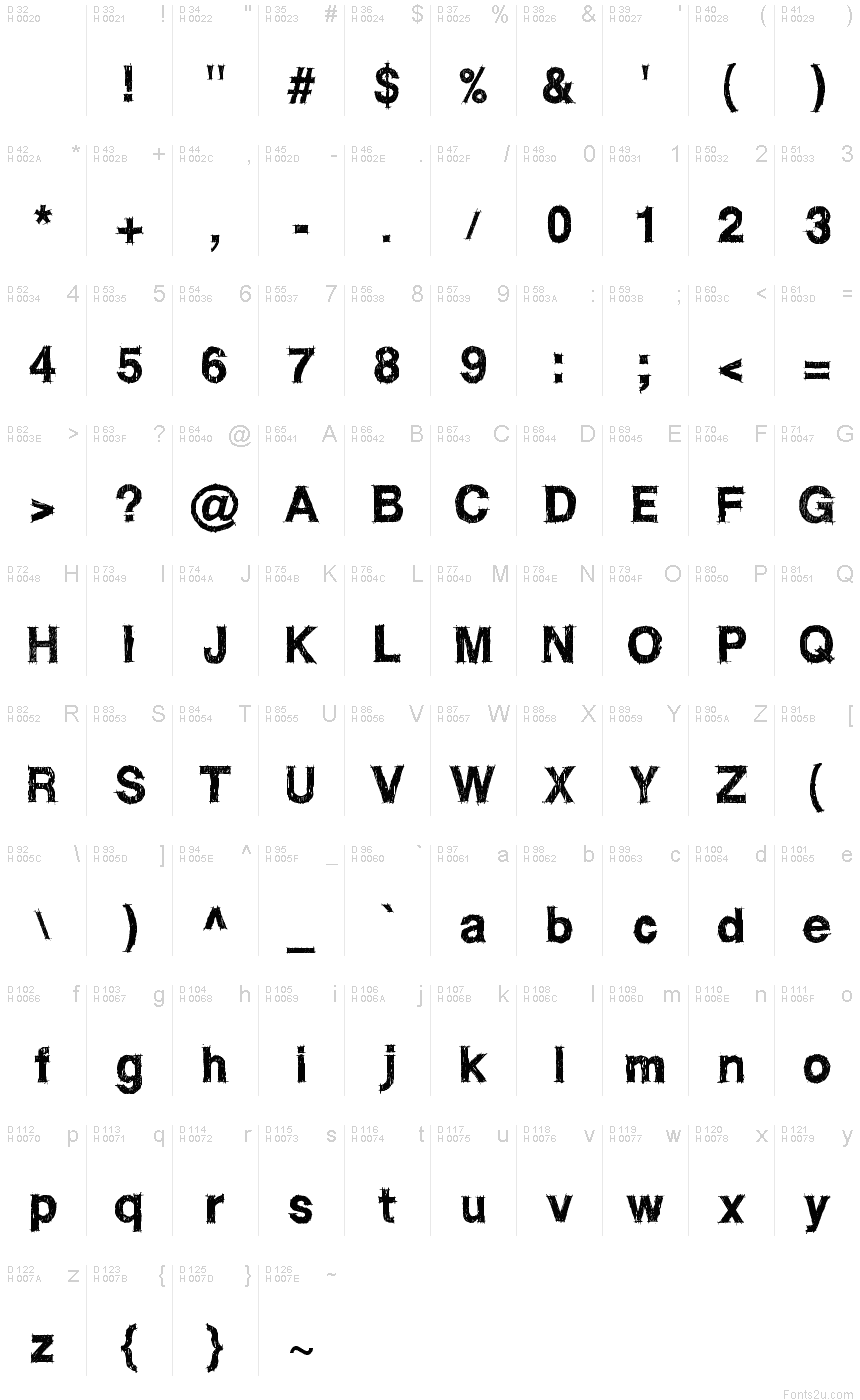
WC ROUGHTRAD Bta
WC Roughtrad to darmowy, erodowany krój typu display o szerokich, pełnych wielkich literach. Postrzępione krawędzie i gęste zadrapania sprawiają, że litery wyglądają na oskrobane, wyszczerbione i zniszczone przez warunki atmosferyczne. Ich solidne proporcje sprawiają, że stylizowany na zniszczony wygląd ma charakter wyrazisty, a nie delikatny.
Plakaty to jego najbardziej oczywiste zastosowanie, zwłaszcza w przypadku wydarzeń przemysłowych, muzyki undergroundowej czy rozrywki o tematyce akcji. Nadaje się również do gadżetów i grafiki gier, gdzie uszkodzone napisy mogą stać się częścią zużytego szyldu, wytłoczonego emblematu lub zniszczonego interfejsu.